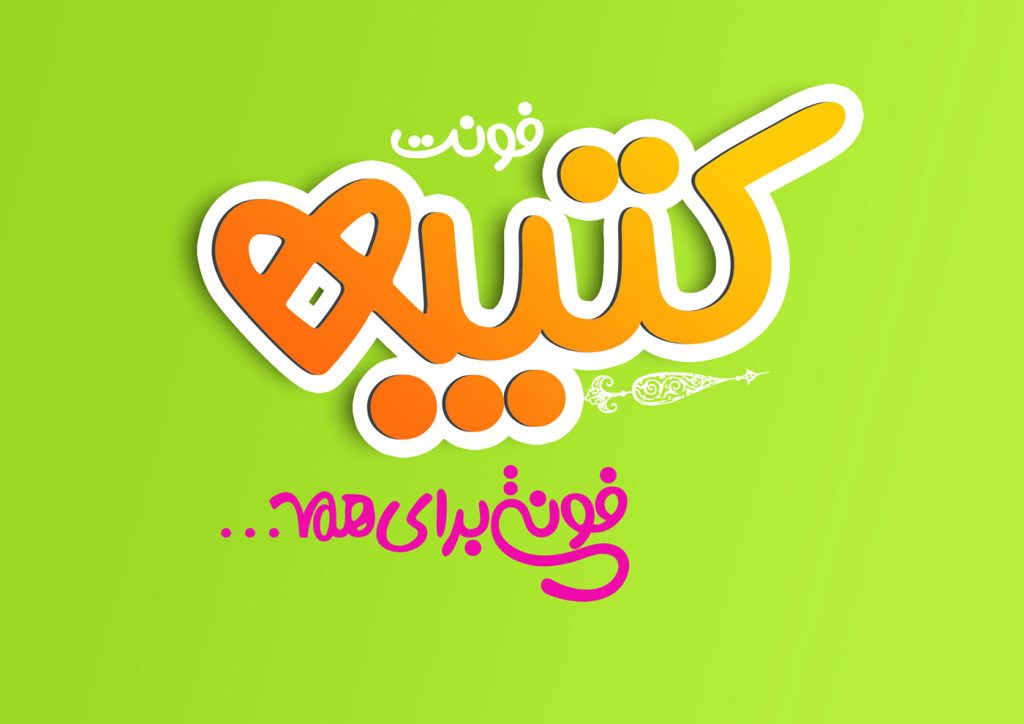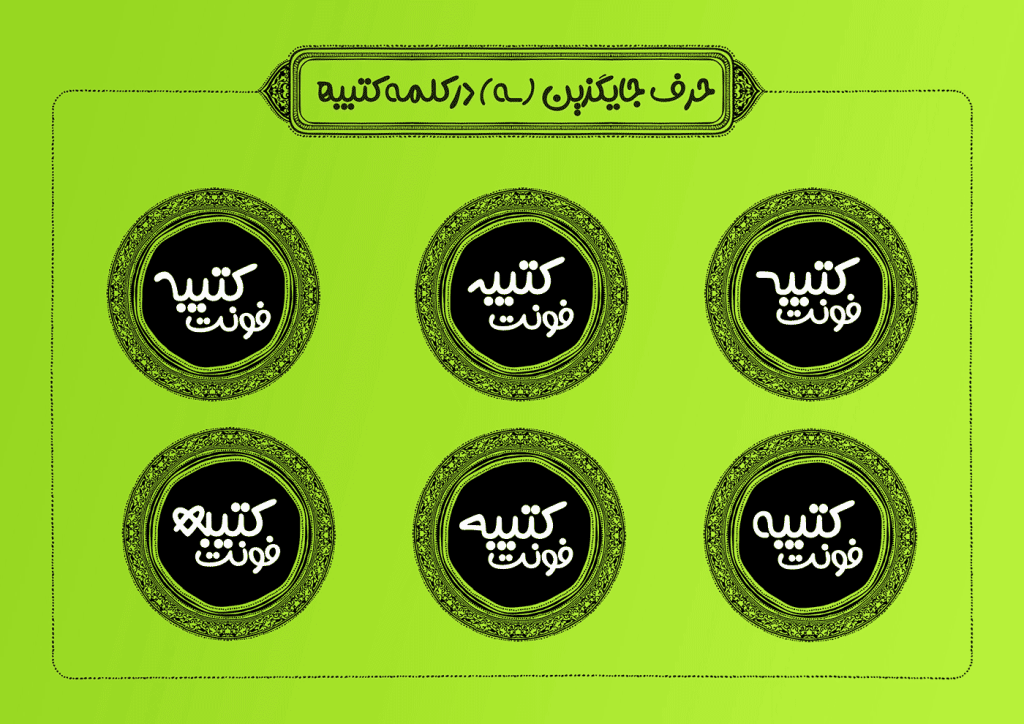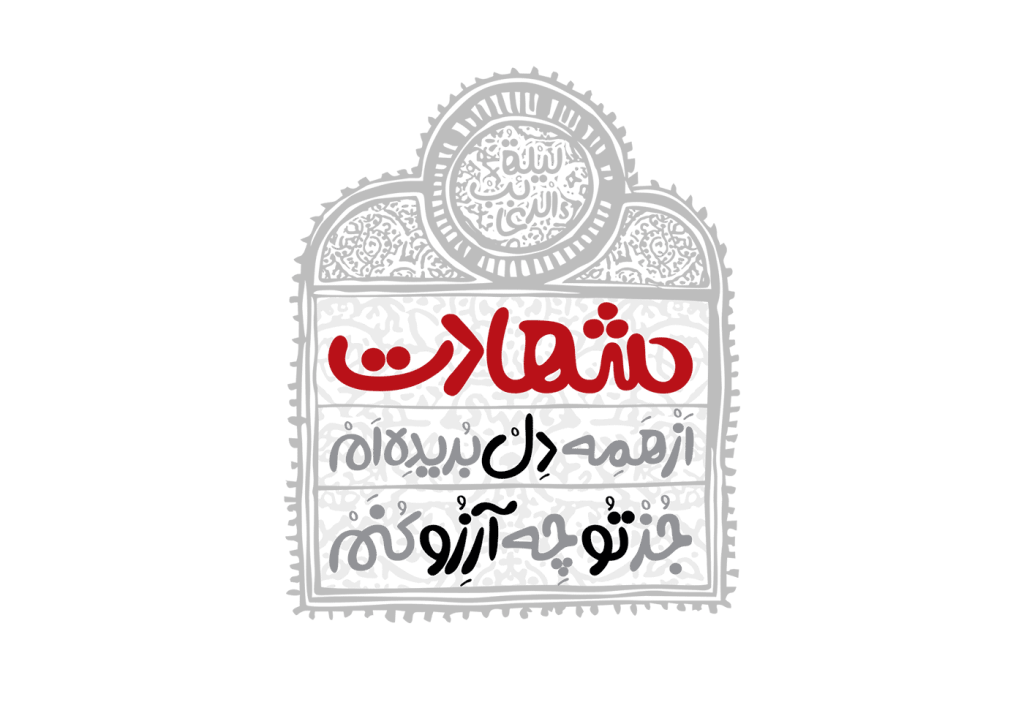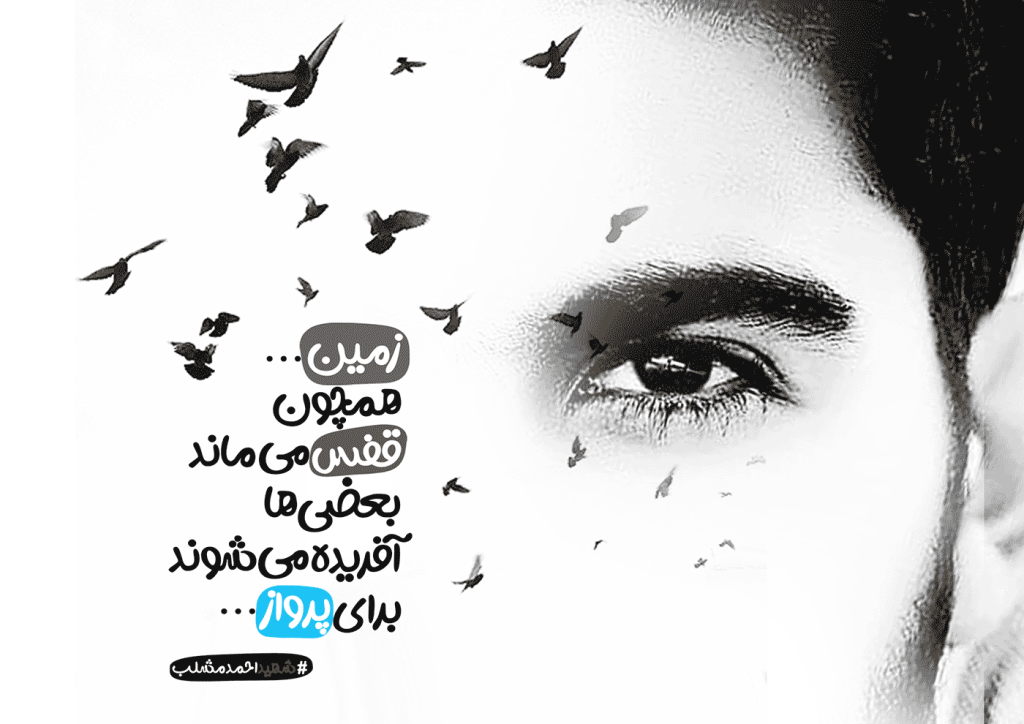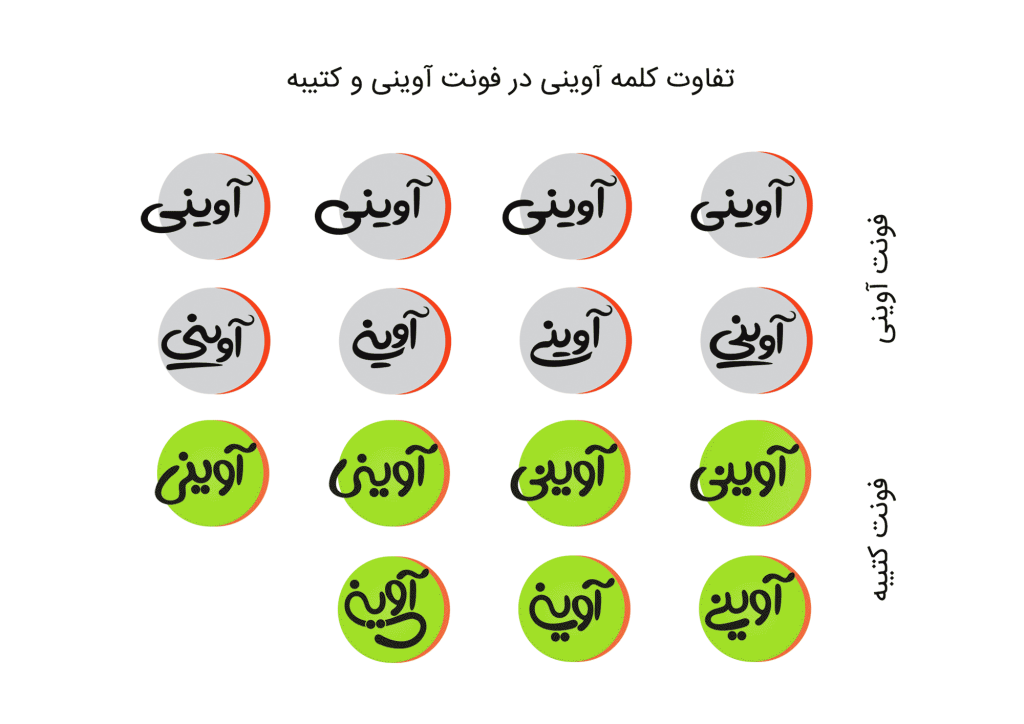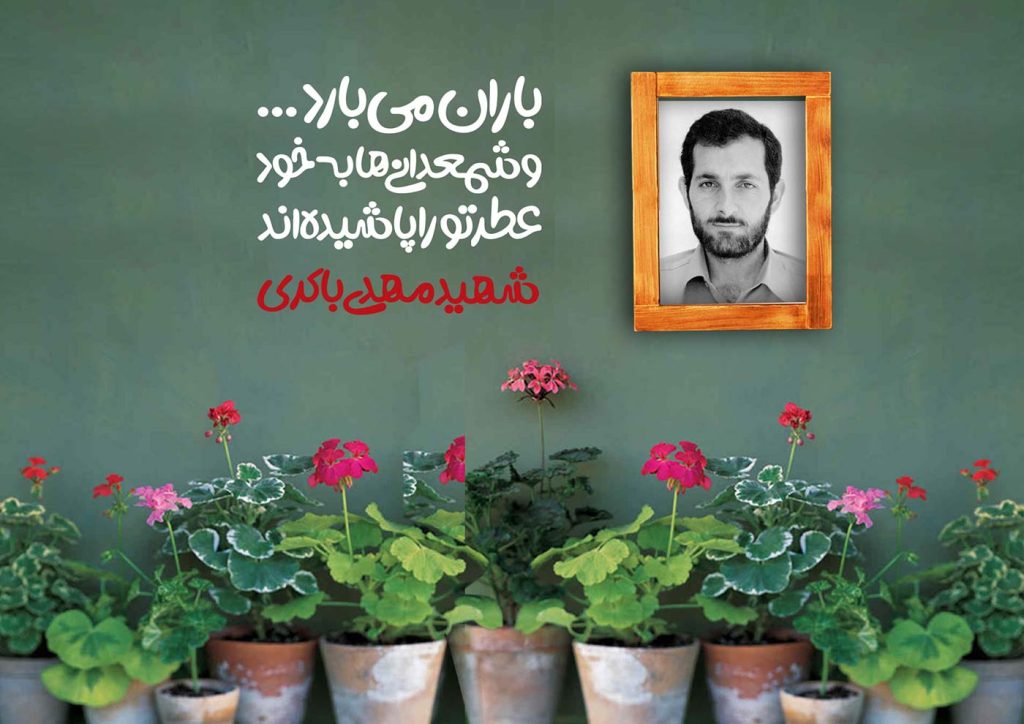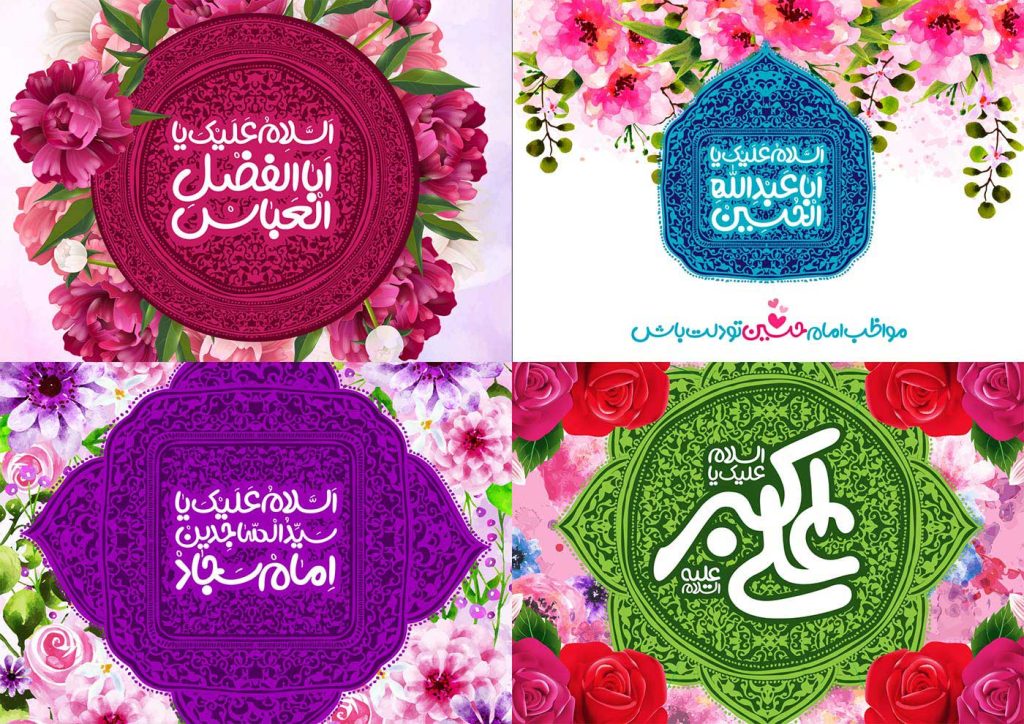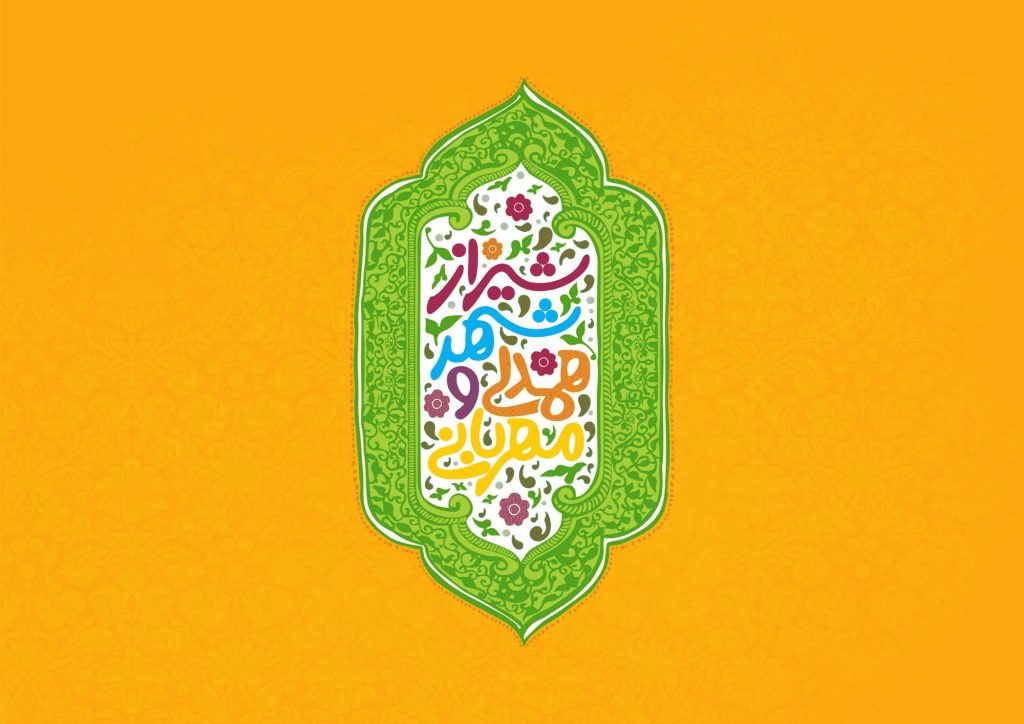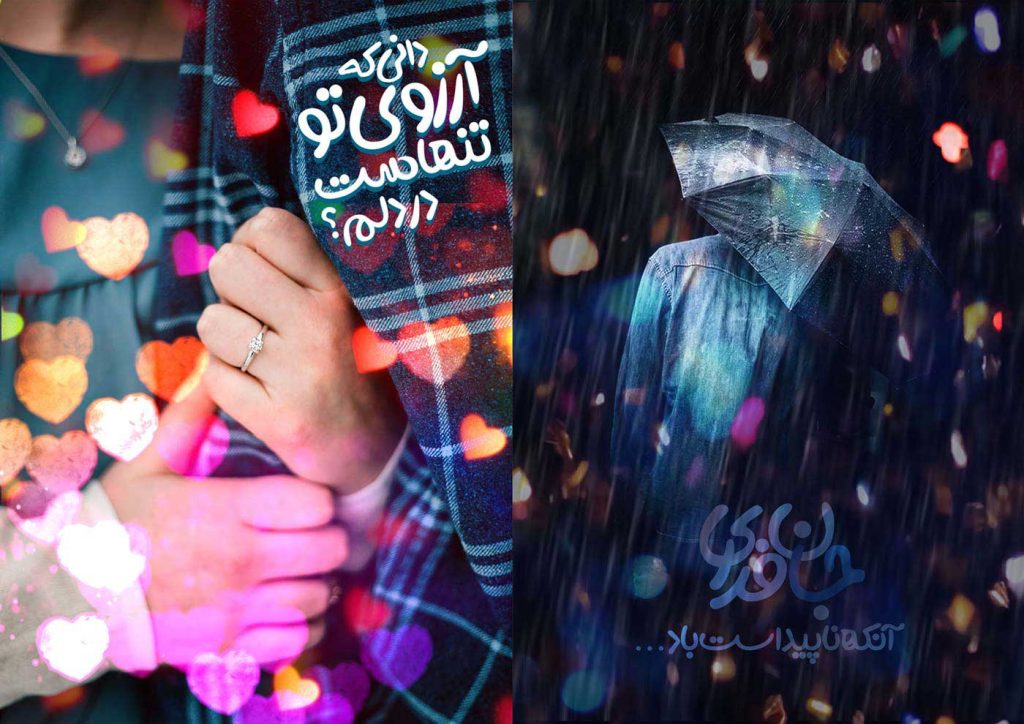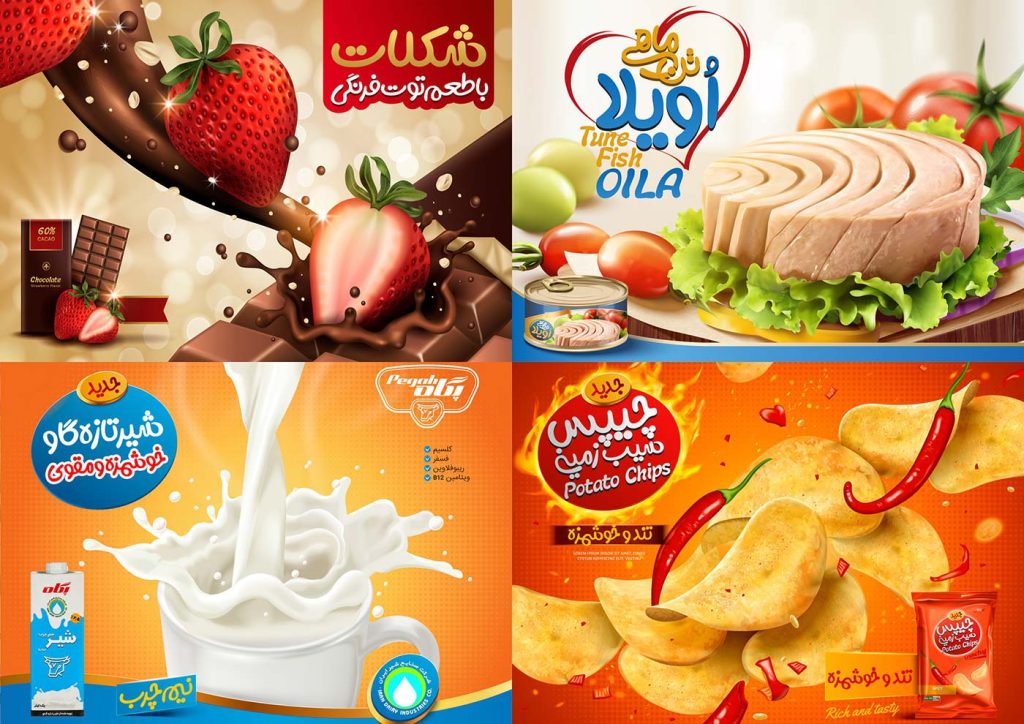
فونت کتیبه
اگر به گذشته رجوع نمائیم به جرات میتوان فوت آوینی را محبوب کاربران دانست. این محبوبیت به علت حالت دستنویس رها و آزادانه و دیگری ترکیبات جایگزین متعدد بوده است حال آنکه تایپ فیس کتیبه این دو ویژگی مذکور را بسیار بیشتر و پرو پیمانتر در خود جای داده است. به دین معنی که هم اشکال حروف فانتزیتر و و شورانگیز تر از آوینی است و هم تعداد حروف جایگزین و ترکیبات نیز بیشتر از آن می باشد.
برای فهم و دریافتن از ویژگیهای گفته شده این قلم توصیه میکنیم تصاویر و توضیحات در ذیل مشاهده فرمائید.
قبلا هم گفتیم که کتیبه دارای ترکیبات جایگزین متعددی است که طبق راهنما میتوانید آنها را تغییر داد. مثلا در تصاویر زیر به تنوع حرف ” ه” در کلمه کتیبه توجه کنید.
قاسم نجاری پیش از این، فونت پرطرفدار آوینی را طراحی کرده است. به تنوع حرف “ی” در فونت آوینی و کتیبه توجه کنید.
تعدادی طرح کتیبه هم موجود است که بصورت برداری میتوانید آنها را وارد نرم افزار نمائید.که دارای حال و هوای نقوش اسلامی و سنتی است که برای همنشینی بهتر با فونت کتیبه دارای سبک آزاد اجرای دستی است.